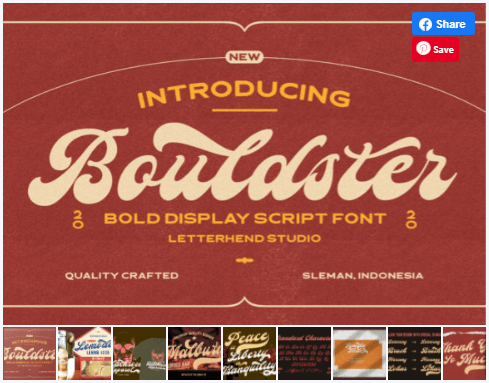
Bouldster Font
Bouldster - это восхитительный и смелый рукописный шрифт, созданный для придания стильности вашим заголовкам и проектам логотипов. Этот шрифт выглядит сильным, уверенным и динамичным и может добавить ностальгический характер вашему дизайну.